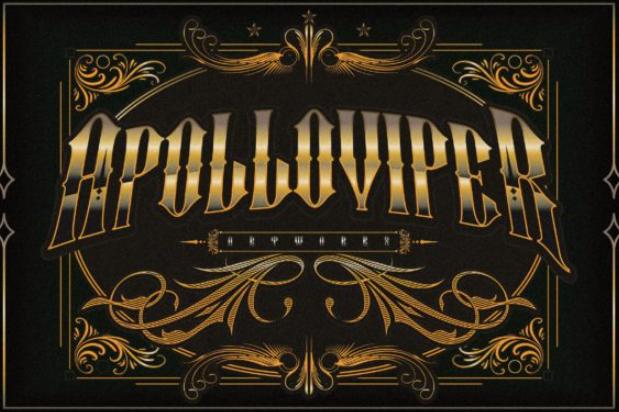
[Creativefabrica] Alifapolloviper Font (dignity.std)
Alifapolloviper - красивый черный шрифт. Используйте этот шрифт для любого проекта, который требует индивидуального оформления!